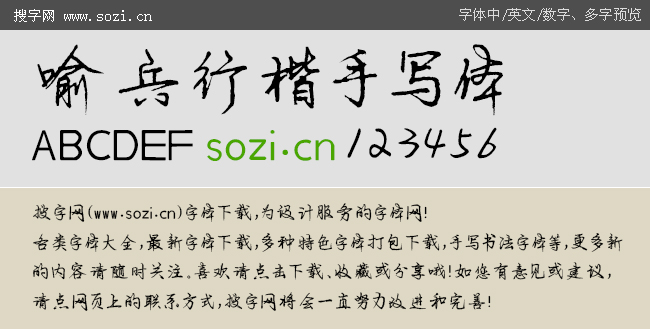
喻兵行楷手寫體
搜字網(wǎng)給大家提供一款喻兵行楷手寫體中文字體下載,喻兵行楷手寫體是一款手寫風(fēng)格的硬筆書法字體。喻兵行楷手寫體書寫流暢自然,字體簡潔大方,是一款視覺效果非常不錯的行楷書法字體,適合網(wǎng)頁設(shè)計、海報設(shè)計、包裝設(shè)計等應(yīng)用。